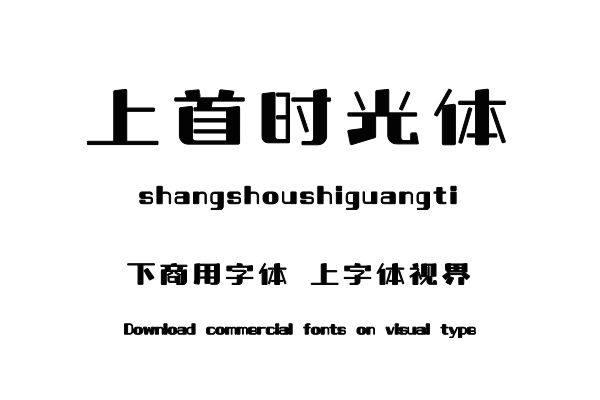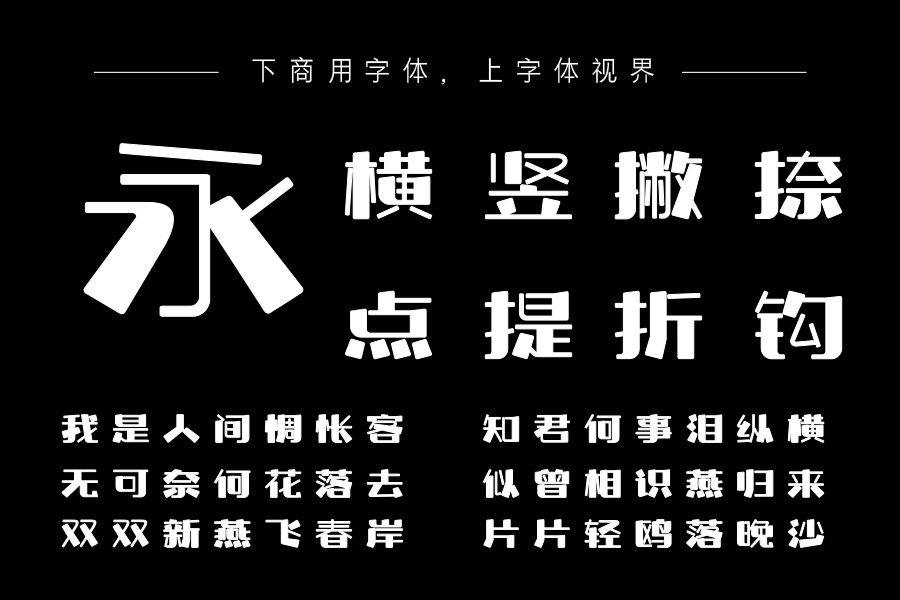
上首时光体,整体字形方正,符合常规的字形,在字体设计时,对字体的笔划进行了设计,设计了粗细两种笔划,对笔划进行导圆,两种笔画共同构成单字,使得字的外部形态上具有......购买须知:“下载服务费”与“字体VIP”所获得字体 仅用于个人非商用, 商用请联系付费授权。本字体为电脑用字,手机没有root权限不支持直接手机换字(手机如何root,请自行百度搜索教程)。购买前请先 了解清楚后再付款 ,字体为虚拟产品无法回收 一旦购买不支持退款。